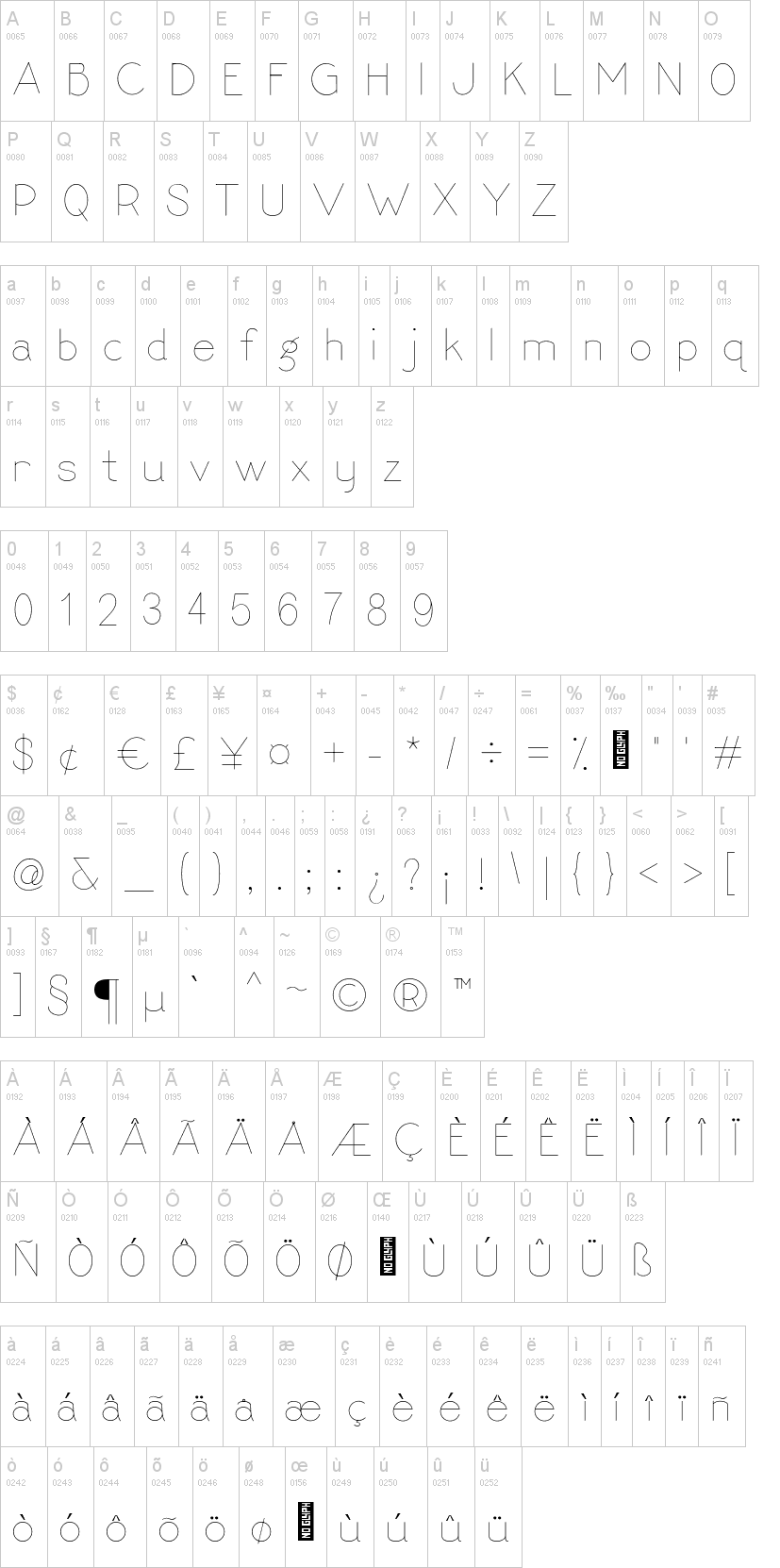
Ngosngos Sans
? Ngosngos Sans 是一款由南非设计师罗伯特·纳克斯(Robert Nacks)设计的一款非常特别的字体。它具有独特的非洲气息,结合了南非传统文化的精华。它的字体笔画简洁,易读性强,适合用于商业广告和宣传物料的设计。它的设计风格既活泼又细腻,可以让您的文字更加生动有趣,从而更好地吸引读者的注意力。
Ngosngos Sans是一款非常不错的手写艺术字体,具有很好的视觉感,适合于文化类的宣传设计、商业类品牌的广告和产品包装设计以及个性化文字排版等较多场景。